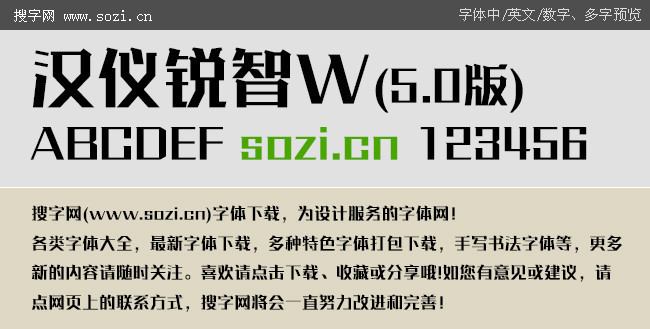
漢儀銳智5.0
搜字網(wǎng)提供一款漢儀銳智5.0中文字體下載,漢儀銳智是一款非常有個(gè)性的藝術(shù)字體,字體結(jié)構(gòu)醒目,簡(jiǎn)潔大方,非常有特色,能夠適用于藝術(shù)設(shè)計(jì)、包裝印刷、簽名設(shè)計(jì)、圖形設(shè)計(jì)等領(lǐng)域。(如需要商用請(qǐng)聯(lián)系漢儀字庫購(gòu)買版權(quán))